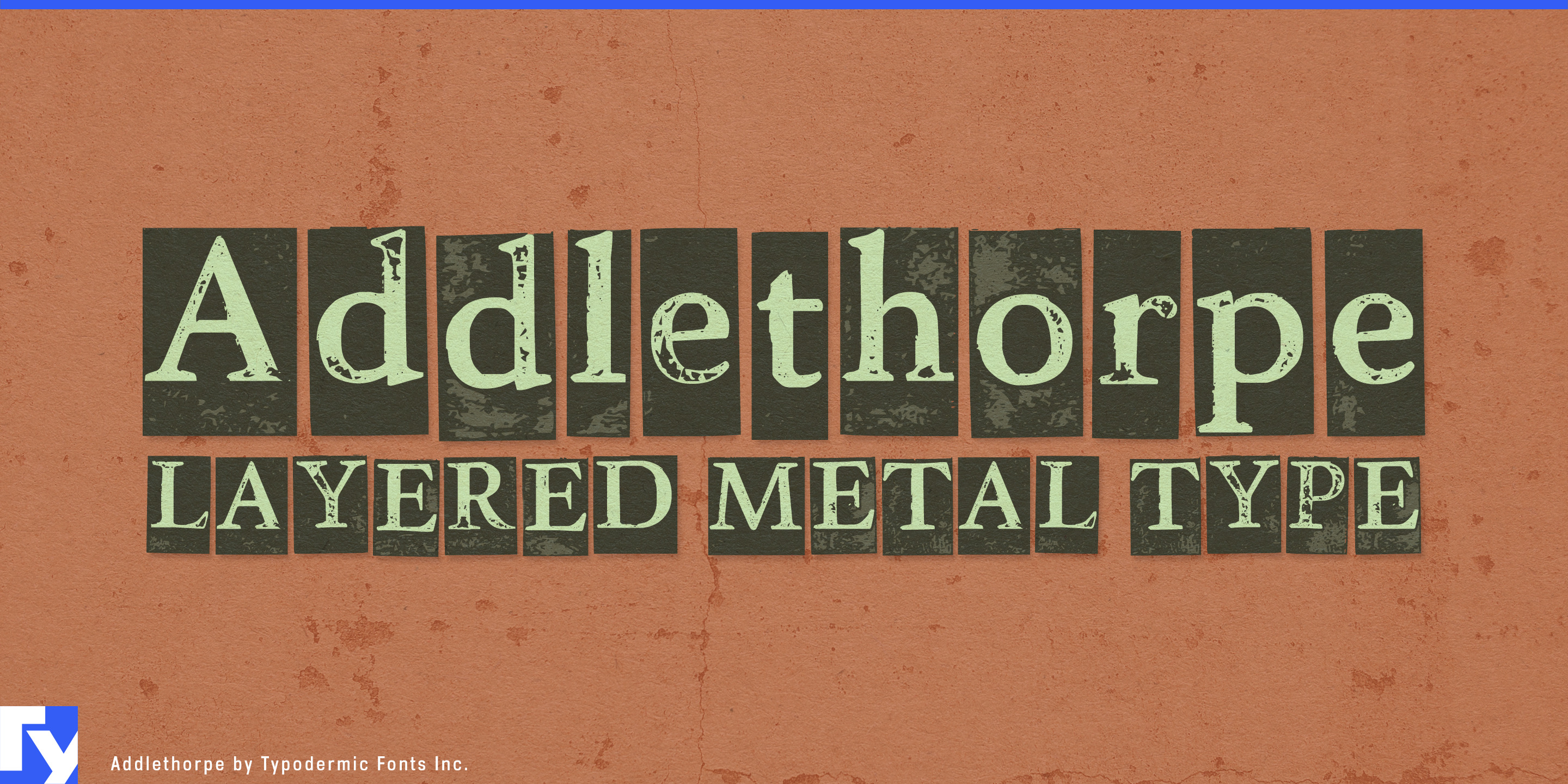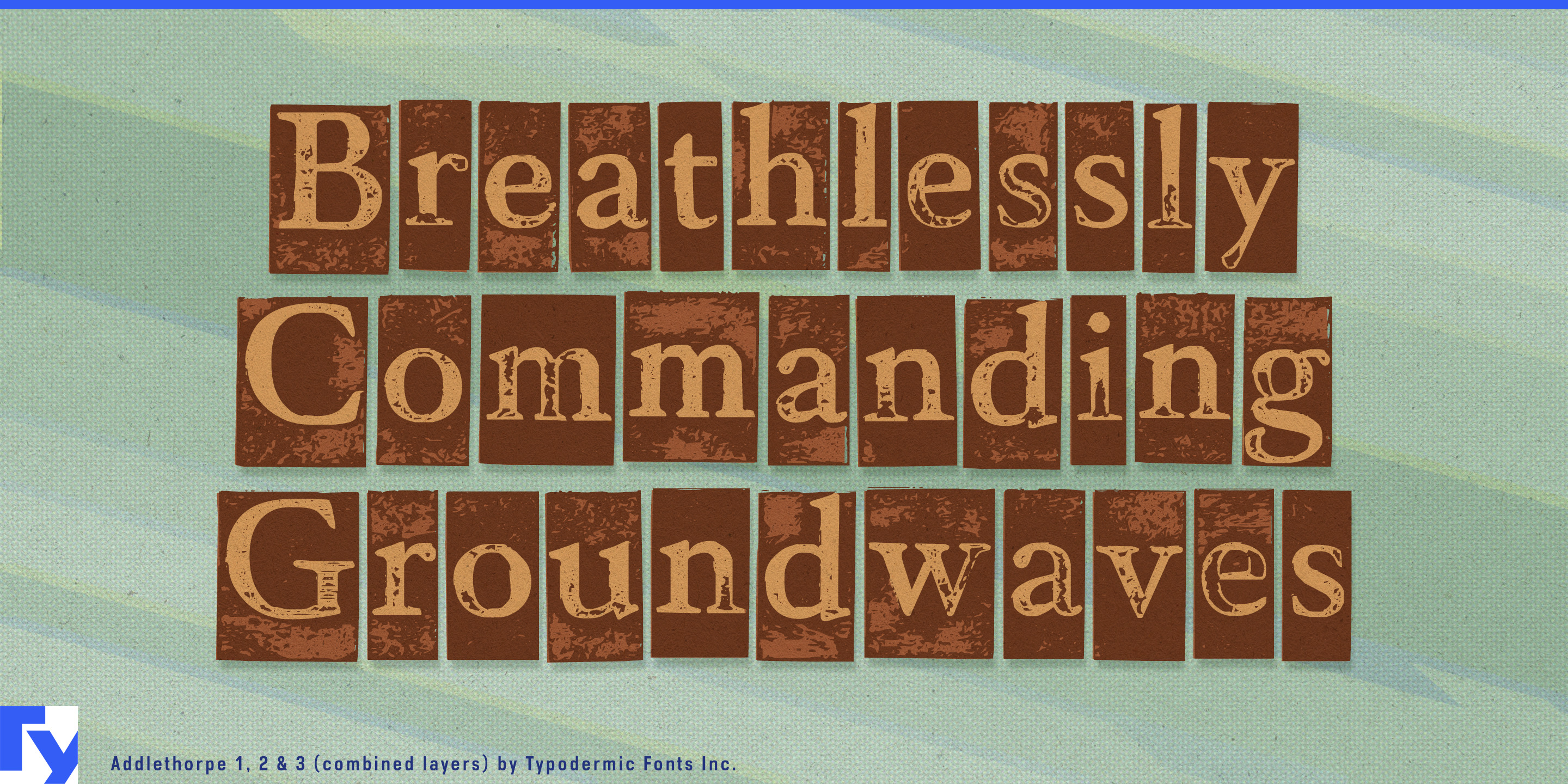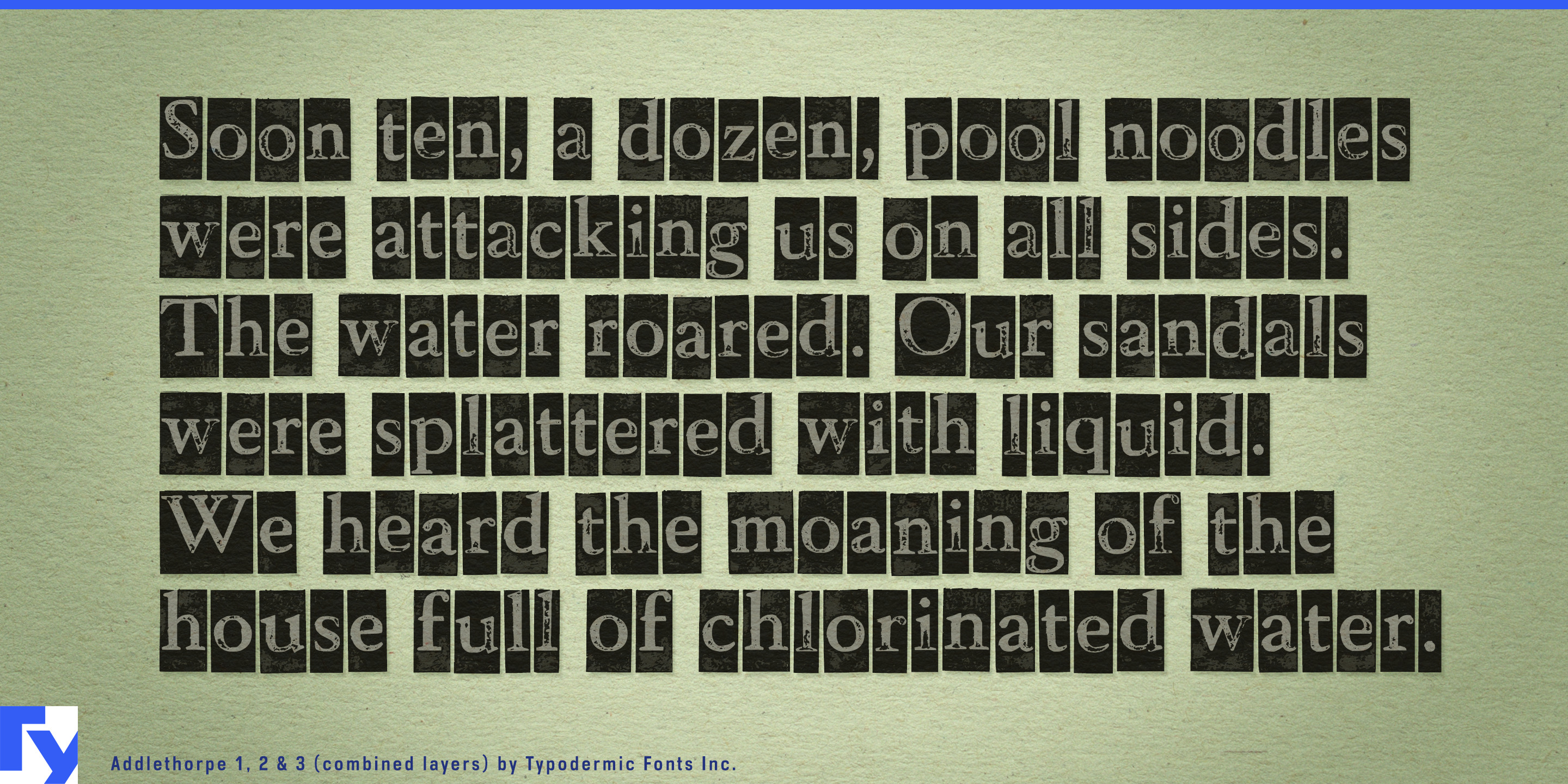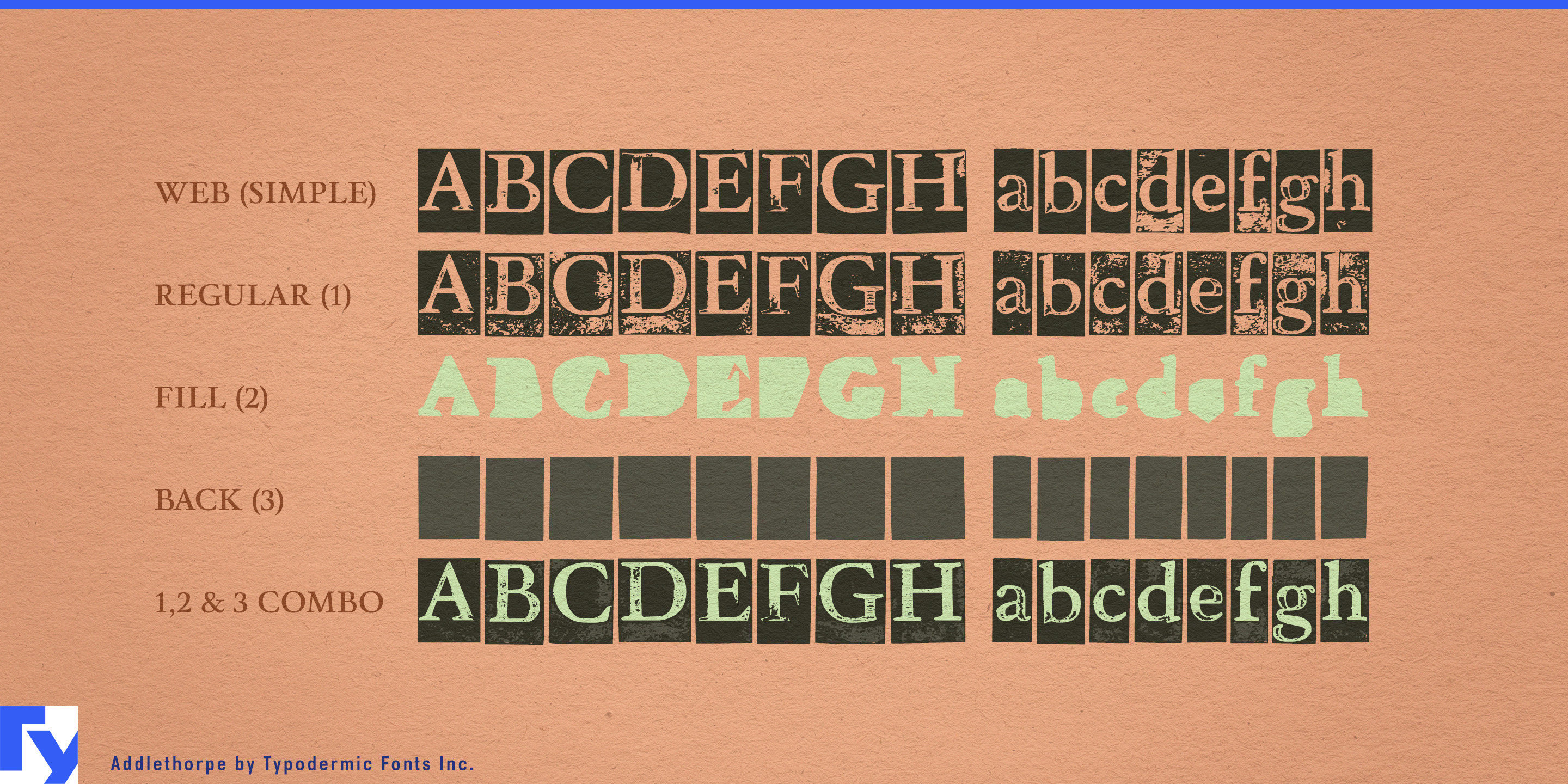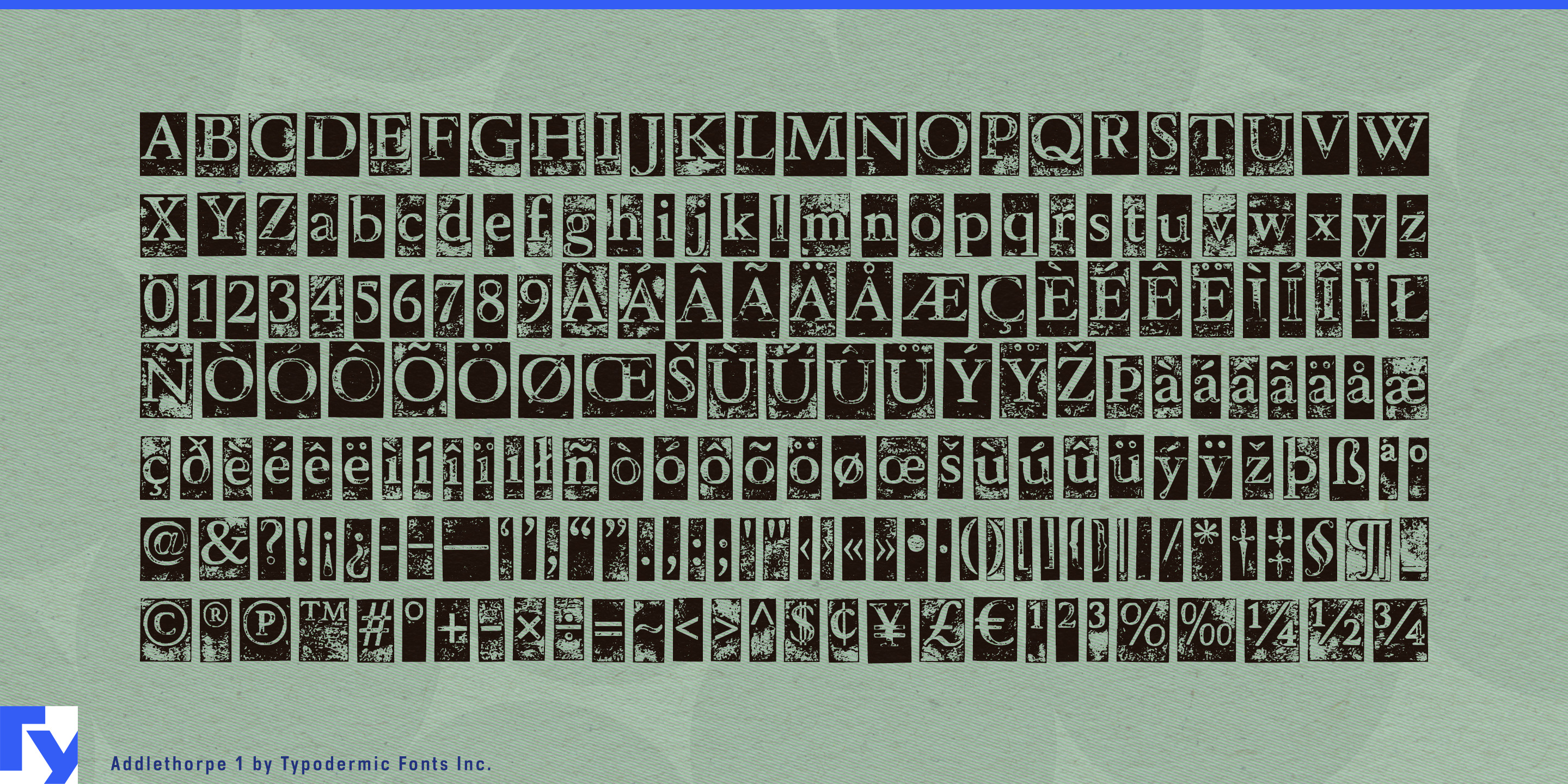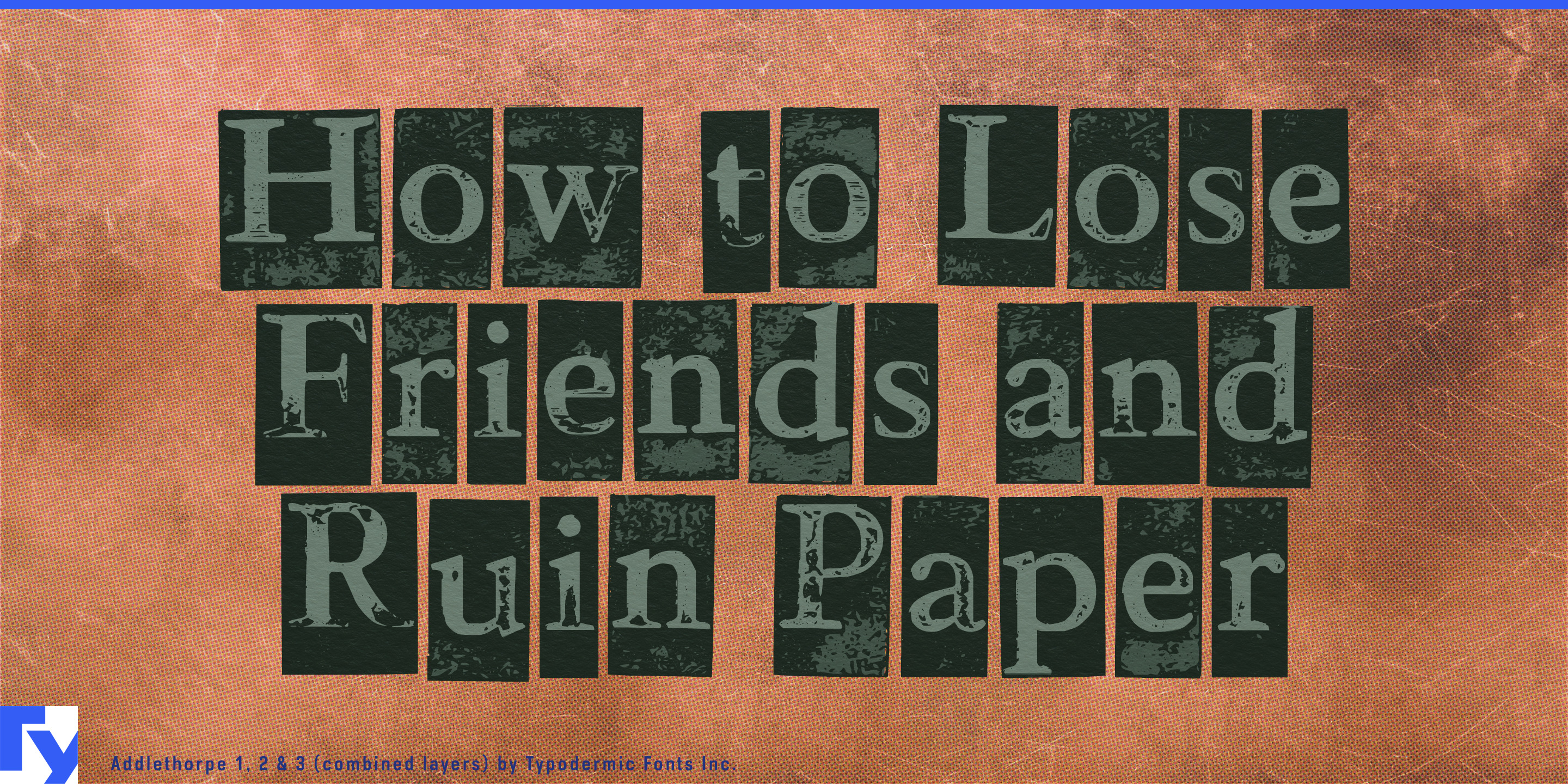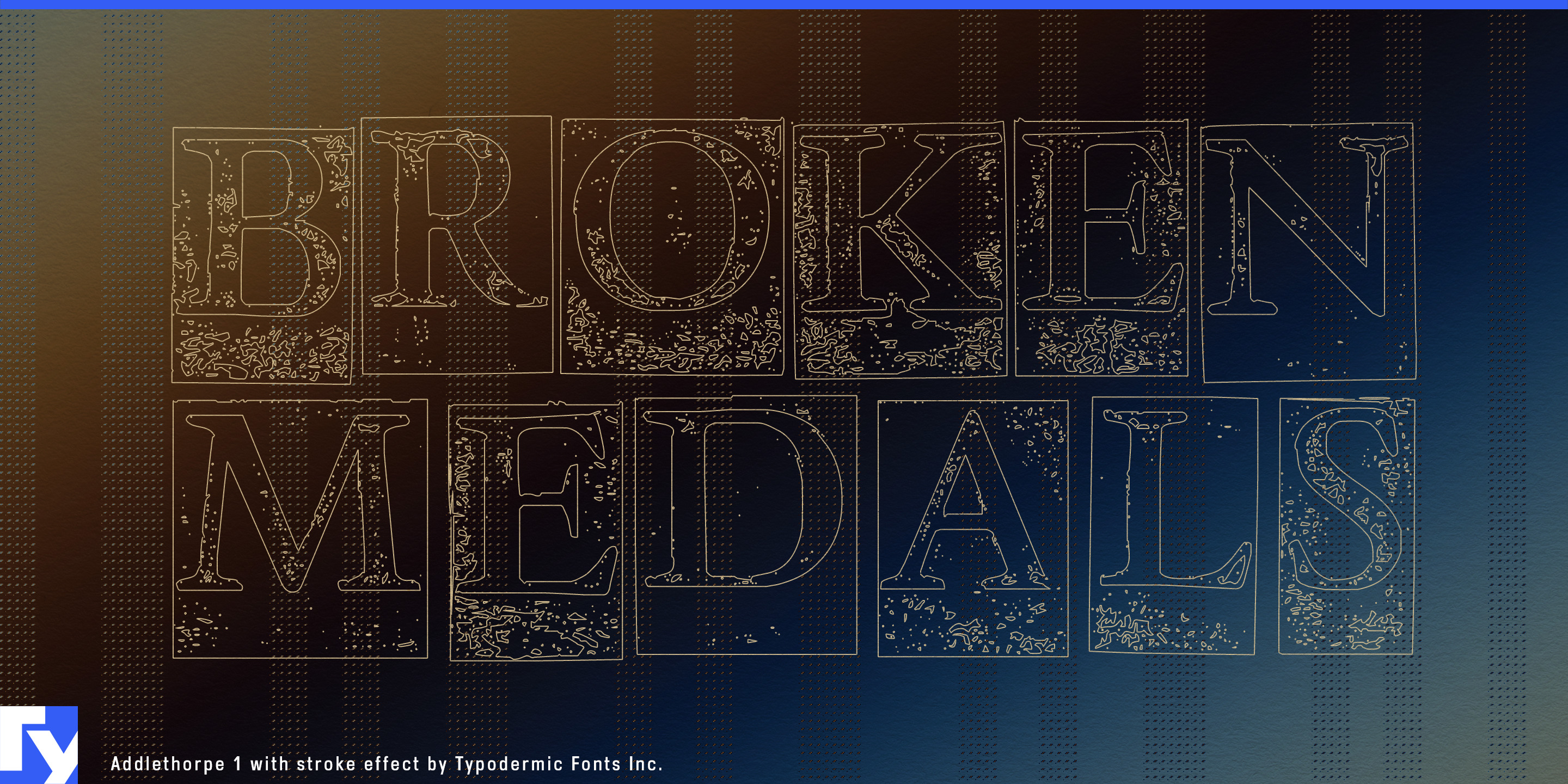
Addlethorpe
かすれた書体の多くは、印刷で残る跡を模しています。Addlethorpeはその一歩手前に戻り、跡を生むもの自体を見せます。一文字ずつ傷んだ金属ブロックに載っているため、単語は後から質感を加えた滑らかな輪郭ではなく、物理的な部品を並べた列に見えます。文字、塗り、背面のレイヤーは別々に組み合わせ、色を変え、位置をずらせます。組み立てた感じ、版ずれ、立体感をどう見せるか、デザイナーが細かく調整できます。
そのため、Addlethorpeは特殊印刷やパッケージ製造に特に有用です。製紙会社、ラベル加工会社、箔押し・エンボス加工会社、インクメーカー、印刷仕上げ会社なら、印刷見本市のブース壁面、見本帳の表紙、新素材の発表、色見本キット、工場見学のグラフィック、パッケージ賞の展示に使えます。レイヤーごとにブランドや工程の色を割り当てれば、単一のかすれた表面に埋もれず、文字の構造を見せられます。
レイヤー構造はモーショングラフィックスにも応用できます。展示会のスクリーン、発表映像、製造工程のデモンストレーションでは、ブロック、塗り、印刷面を分離し、動かし、組み直せます。文字を静止した効果ではなく、部品の集合として扱えます。
循環型の建材も、現代的な用途の一つです。建築部材の再利用会社、回収したレンガの供給業者、マテリアルバンク、リユース市場が扱う部材には、以前の用途、不規則な表面、一つひとつ異なる来歴があります。Addlethorpeの文字も視覚的にはそれに似ています。単語が、一体で完璧に製造されたものではなく、使い込まれた個別の部品から組み立てられて見えるのです。素材ライブラリーの壁面、古材倉庫のグラフィック、再利用部材のカタログ、リユース展示館の見出しでは、ありきたりなリサイクルの図像に頼らず、その考えを伝えられます。
モジュール式の内装システムにも関連した役割があります。吸音パネル、取り外し可能な間仕切り、モジュール棚、プレハブ内装は、繰り返すユニットを組み合わせて大きな構造をつくります。Addlethorpeは、書体の個々のブロックが製品のモジュール構造と呼応するような、製品ファミリー名、ショールームのグラフィック、構成例の表示、建築見本市の見出しに使えます。
印刷の歴史を扱う場面にも、文字どおり適しています。タイポグラフィ展、出版社の記念企画、ブックアートのプログラム、印刷博物館、機械式組版のドキュメンタリーでは、活字そのものの物質感を、古風なセリフ体でほのめかすだけでなく、はっきり見せたいときに使えます。
Addlethorpeは、部品という考えが重要な場面に向いています。印刷工程、モジュールシステム、再利用素材、製造現場、ものづくりを扱う展示などです。完成した印字だけでなく、その下にある構成要素まで見せます。